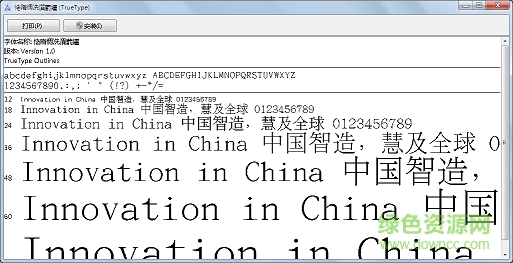
bousungeg light gb字體是一款ttf格式的文鼎報宋簡字體,這款字體保持了宋體的共通特點(diǎn),橫細(xì)豎粗,字形周正嚴(yán)謹(jǐn),屬于襯線字體類,常用于正文排版方面!
現(xiàn)代鉛字采用了宋體印刷。后來依據(jù)西方文字的黑體和意大利體的方式,在漢字印刷體中也創(chuàng)造了黑體的鉛字。目前宋體、黑體、仿宋體和楷體成為漢字印刷的主要四種字體。「宋體」是一類字體的總稱,有很多字體都屬于這個范疇。